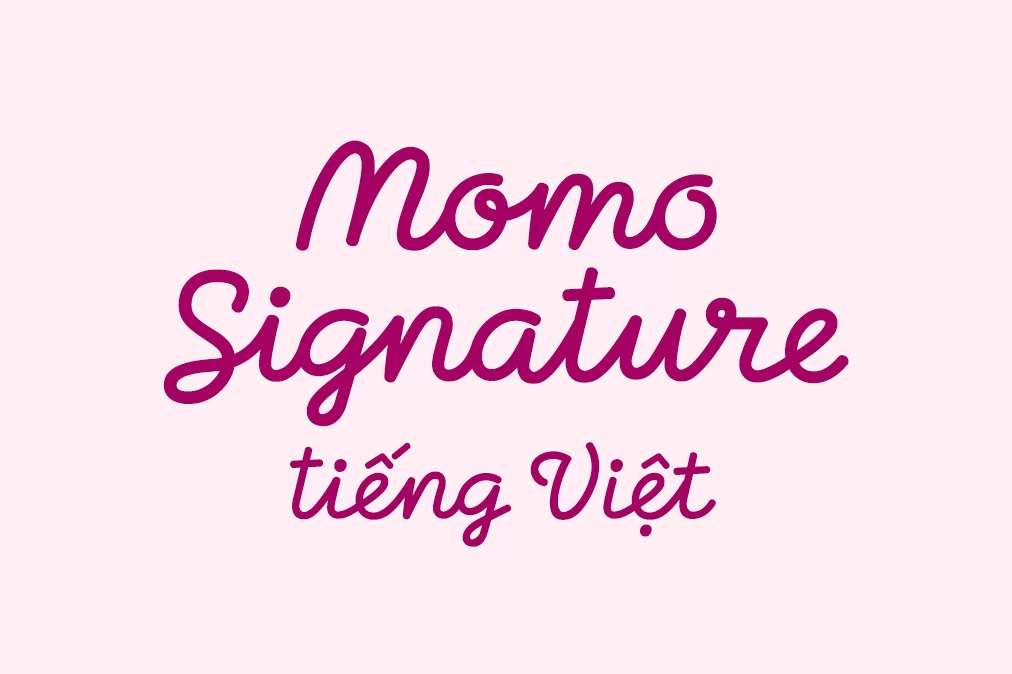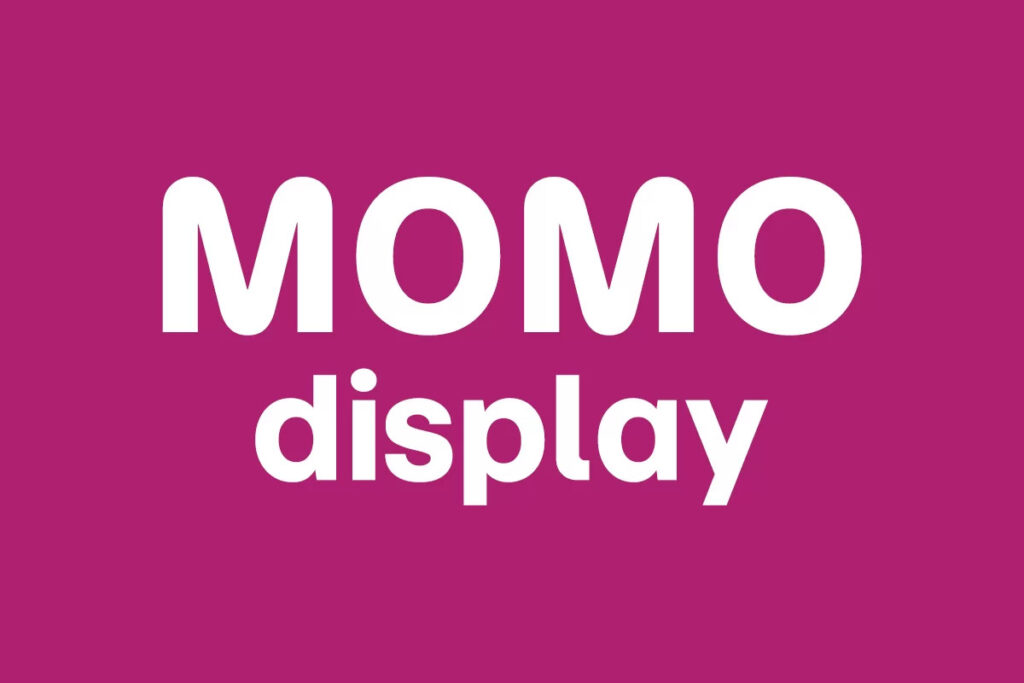
Phông chữ của MoMo, đặc biệt là hệ thống phông chữ MoMo Trust, đã trở nên quen thuộc với người dùng Việt Nam nhờ cấu trúc bo tròn mềm mại và vẻ ngoài trẻ trung. Việc sở hữu font MoMo giúp các nhà thiết kế và đơn vị thi công homestay, văn phòng sáng tạo đồng bộ hóa hình ảnh thương hiệu theo xu hướng công nghệ và sự gần gũi.
Đặc điểm thiết kế của bộ font chữ MoMo
Điểm lôi cuốn đặc trưng của font chữ MoMo nằm ở sự kết hợp giữa phong cách Sans-serif hiện đại và những đường bo góc mịn màng. Cấu trúc chữ được thiết kế với độ mở lớn, khoảng cách ký tự thông thoáng giúp văn bản hiển thị rõ nét trên cả ứng dụng di động lẫn các bản in khổ lớn. Phiên bản Việt hóa xử lý tinh tế các dấu thanh, đảm bảo các ký tự như “đ, ă, ơ” phối hợp hài hòa với khung chữ chính, tạo nên một dòng chảy văn bản mạch lạc và đầy tính thẩm mỹ.
Sự ổn định của font MoMo Trust Sans và Trust Display còn thể hiện qua khả năng truyền tải năng lượng tích cực và sự tin cậy. Trong khi các kiểu chữ không chân truyền thống đôi khi mang cảm giác khô cứng, bộ phông này lại toát lên sự linh hoạt, phù hợp với tư duy kiến trúc mở và các giải pháp xây dựng lắp ghép hiện đại. Đây là lựa chọn phù hợp cho những ai muốn khẳng định cá tính thương hiệu năng động, hiện đại và chú trọng vào trải nghiệm thị giác của khách hàng.
| Phân loại phong cách | Sans-serif / Rounded / Modern |
| Nhóm phông tiêu biểu | MoMo Trust Sans, MoMo Trust Display |
| Mục đích phù hợp | Giao diện App, Logo, Bảng hiệu, Poster |
Tư vấn lựa chọn: Để bản thiết kế đạt được hiệu quả thị giác ổn định, bạn nên sử dụng font momo trust display cho các tiêu đề lớn và font momo trust sans cho phần nội dung thuyết minh. Sự phân cấp này giúp bố cục hồ sơ dự án của bạn trông khoa học và dễ tiếp nhận thông tin hơn.
03 Ứng dụng font MoMo vào thực tế kiến trúc và trang trí
Nhờ diện mạo khoa học và sự gần gũi, bộ phông chữ này mang lại giá trị thực tế cao trong quá trình quảng bá và hoàn thiện công trình hiện đại:
- Hệ thống nhận diện cho Homestay & Cafe: Những nét chữ bo tròn của font chữ của MoMo rất ăn ý khi được gia công cắt nổi trên mica hoặc gỗ sáng màu. Kiểu chữ này giúp không gian toát lên vẻ trẻ trung, thân thiện, thu hút nhóm khách hàng yêu thích công nghệ và sự đổi mới.
- Hệ thống biển chỉ dẫn văn phòng container: Sử dụng phông chữ này cho biển tên phòng hoặc bảng nội quy giúp văn phòng làm việc trở nên chuyên nghiệp và hiện đại hơn, đồng bộ với phong cách kiến trúc Industrial tối giản.
- Thiết kế Poster dự án xây dựng: Với độ hiển thị rõ nét, font MoMo giúp các thông tin về giải pháp vật liệu panel, ưu điểm nhà lắp ghép trở nên dễ đọc, tạo ấn tượng tốt về một đơn vị thi công năng động.
03 lưu ý kỹ thuật khi sử dụng font monospace và font MoMo
Để khai thác hiệu quả vẻ đẹp trung tính của dòng phông này, người thiết kế nên lưu tâm một số lưu ý kỹ thuật sau:
- Phân biệt mục đích sử dụng: Tránh nhầm lẫn phông chữ thương hiệu với các dòng font monospace download. Font Monospace thường dùng cho mã code hoặc bảng tính kỹ thuật cần sự căn lề tuyệt đối của các ký tự, trong khi font MoMo tối ưu cho việc trình bày tiêu đề và nội dung truyền thông.
- Kiểm soát khoảng cách dòng: Do cấu trúc chữ bo tròn có phần đầy đặn, bạn nên thiết lập khoảng cách dòng thoáng một chút để văn bản không bị chồng lấn, giúp tổng thể bản in hồ sơ báo giá trở nên minh bạch hơn.
- Lựa chọn kích thước hiển thị: Font MoMo hiển thị tốt ở hầu hết các kích cỡ, tuy nhiên với các biển hiệu ngoài trời, bạn nên kiểm tra độ sắc sảo của các đường cong để đảm bảo tính thẩm mỹ sau khi thi công thực tế.